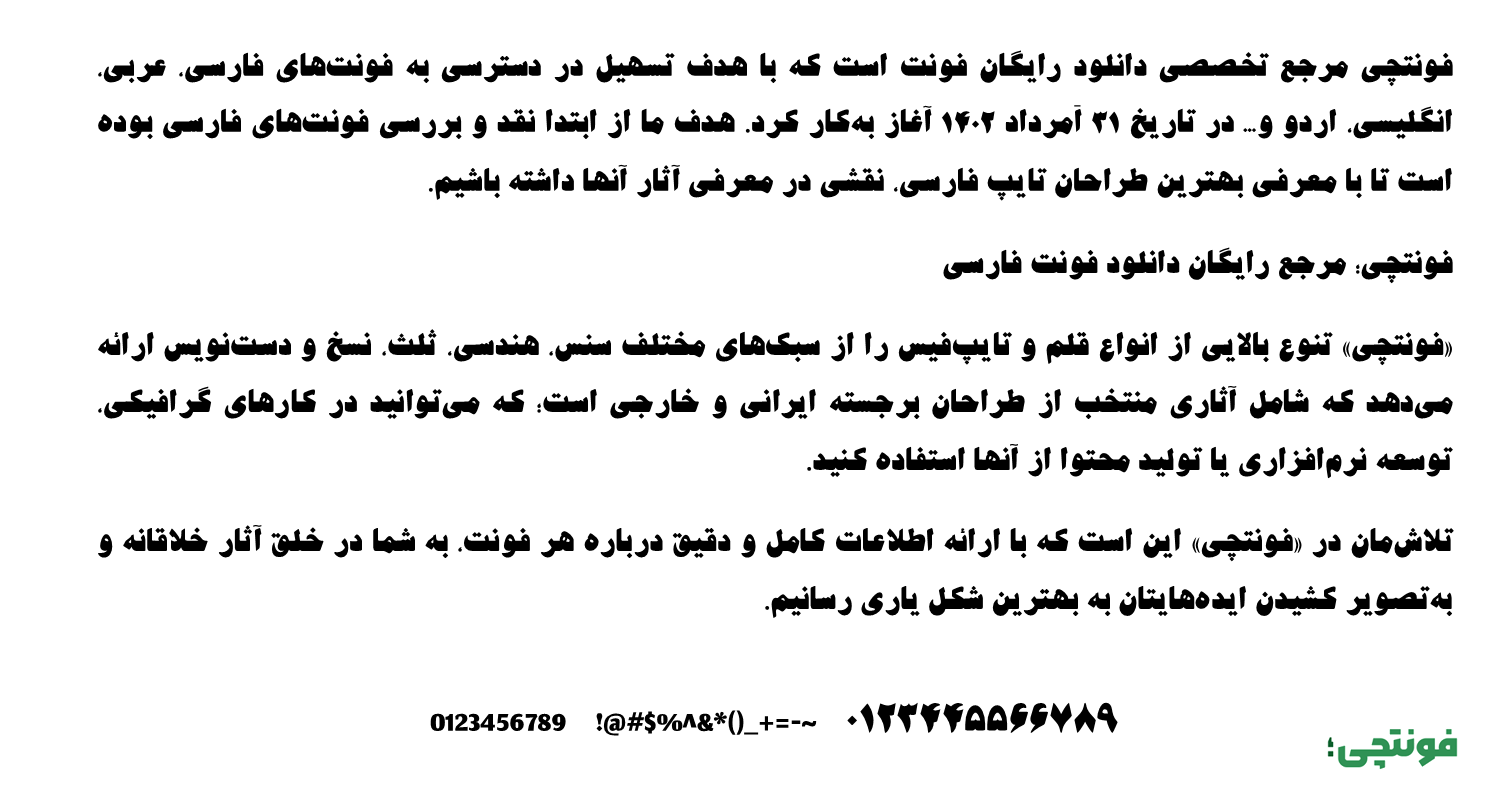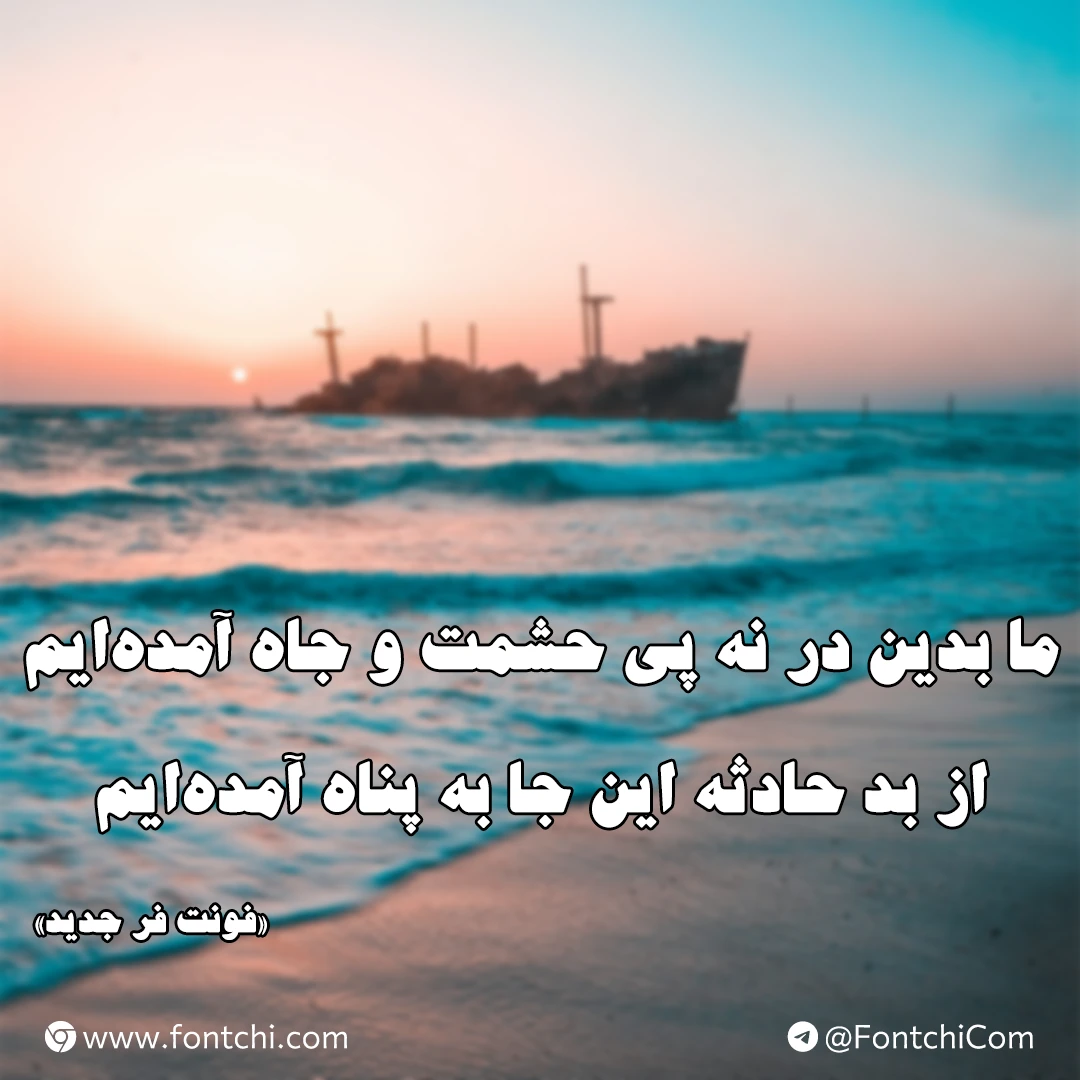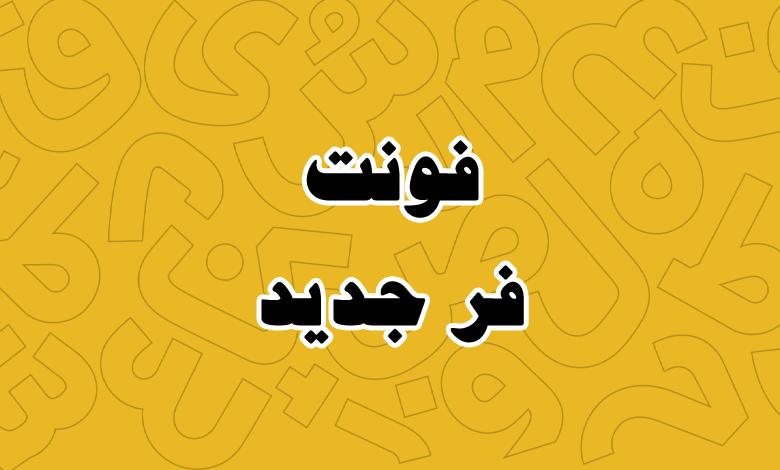
فونت جدید (Far Jadid)
| نام | جدید |
| نام نمایشی | Far Jadid |
| طراح | ابوالفضل سیل سپور |
فونت جدید یا فونت فر جدید (Far Jadid) از سری فونتهای رایگان طراحی شده توسط ابوالفضل سیل سپور است که میتوانید در متون کوتاه و عناوین از این فونت استفاده کنید. در این صفحه نسخه ضخیم این فونت که دارای ظاهری سیاه است را برای دانلود قرار دادهایم.
فونت جدید فر با سبک نسخ طراحی شده است و همانطور که در نمونه متن در تصویر زیر میبینید، برای استفاده در متون کوتاه مناسب است. از جمله عناوین و شعارهای تبلیغاتی که بیشتر در حوزه چاپ و مطبوعات کاربرد دارند.
نقد و بررسی فونت جدید فر (Far Jadid)
فونت جدید فر از زبان فارسی پشتیبانی کاملی داشته و برای این زبان طراحی شده. اما میتوانید برای زبان عربی نیز به صورت محدود از آن استفاده کنید. بهطوری که اعراب و کاراکترهای تزئینی برای هر دو زبان، دارای همنشینی استاندارد هستند. اما در بخش اعداد شاهد کاستی هستیم که از اعداد عربی «٠٤٥٦» پشتیبانی نمیکند.
برای زبان انگلیسی نیز این فونت فاقد طراحی اختصاصی بوده و از فونت پیشفرض سیستم عامل استفاده خواهد کرد. از اینرو برای متون دو زبانه مجبور هستید از یک فونت انگلیسی دیگری که مناسب آن باشد استفاده کنید.
کاربردهای متنوعی برای فونت جدید وجود دارد که متناسب با نیازتان میتوانید استفاده کنید. اما با توجه به ساختار نسخ که این قلم دارد، بیشترین استفادههای آن عبارتند از:
- جلد کتاب و مجلات که نیاز به فونت سیاه داشته باشید.
- استفاده در صنایع چاپ مانند بیلبوردهای تبلیغاتی یا بنرهای محیطی.
- استفاده برای تامنیل شبکههای اجتماعی که عموما مرتبط با موضوعات تاریخی باشد.
- استفاده در متون کوتاه و عناوین شامل شعارها.
- استفاده به عنوان زیرنویس فیلم و سریال در نمایشگرهای بزرگ.